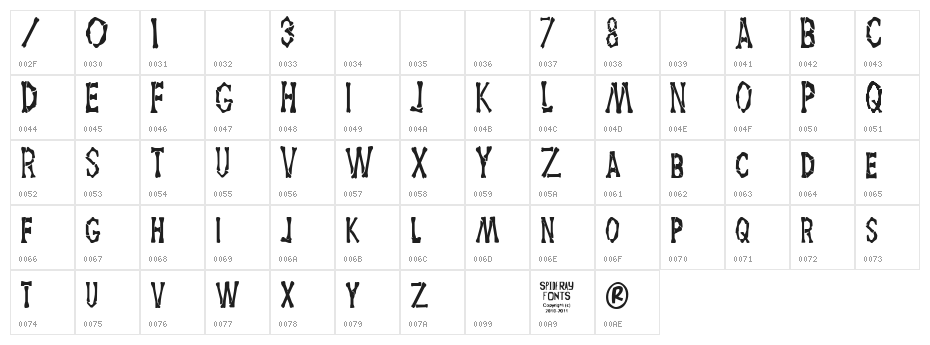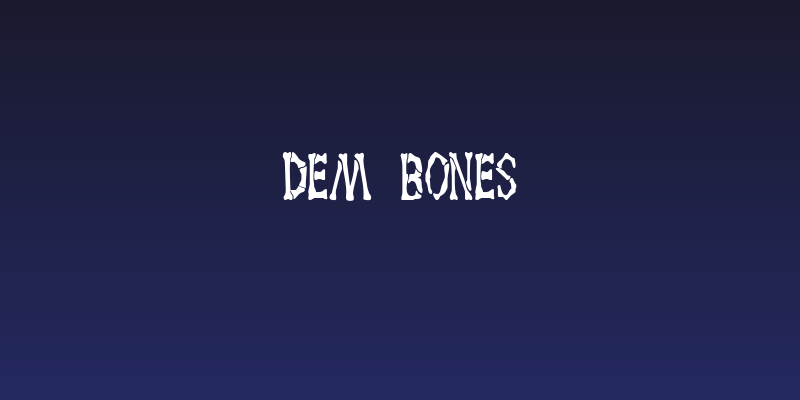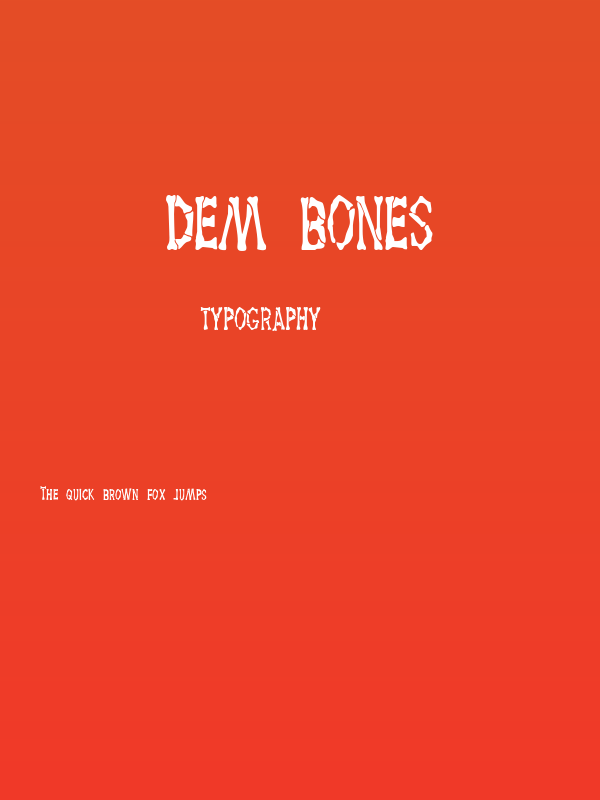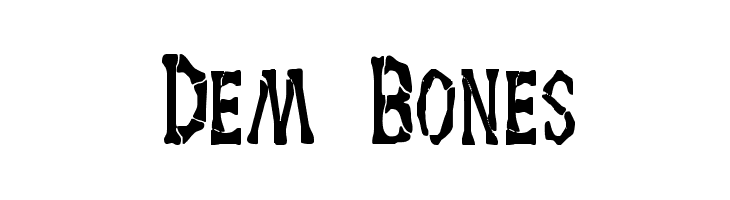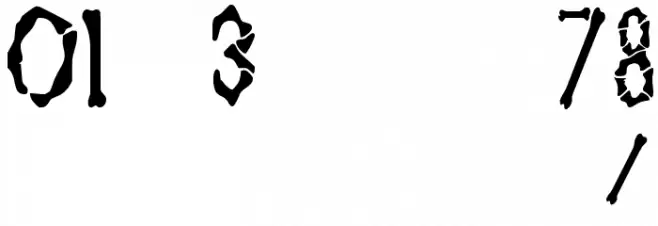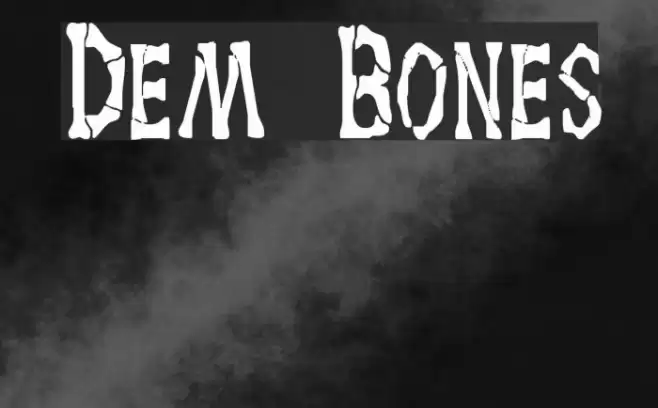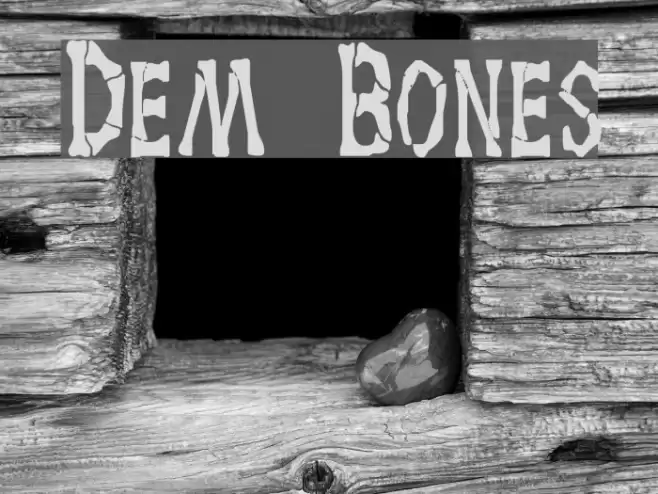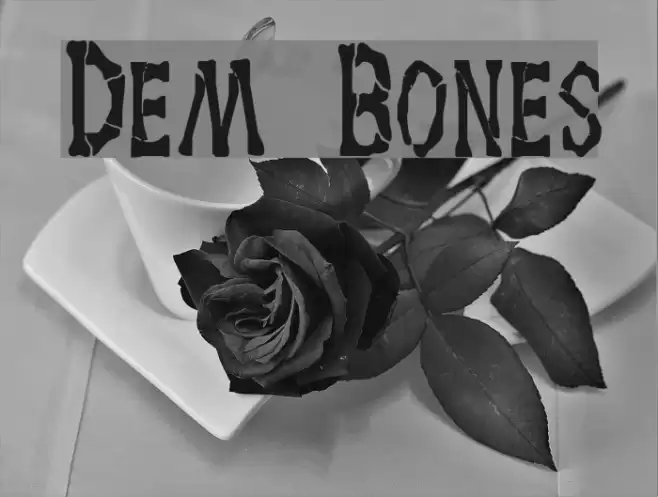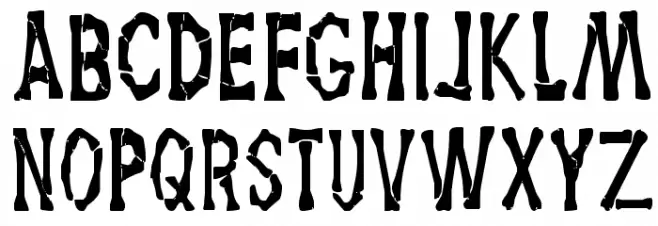
Dem Bones Font
| Anwendungsfall | Headlines, Logos, Themed Invitations |
| Vorgeschlagene Projekte | Ideal for Halloween invitations, themed party decorations, children's book titles, and any project requiring a quirky, spooky aesthetic. |